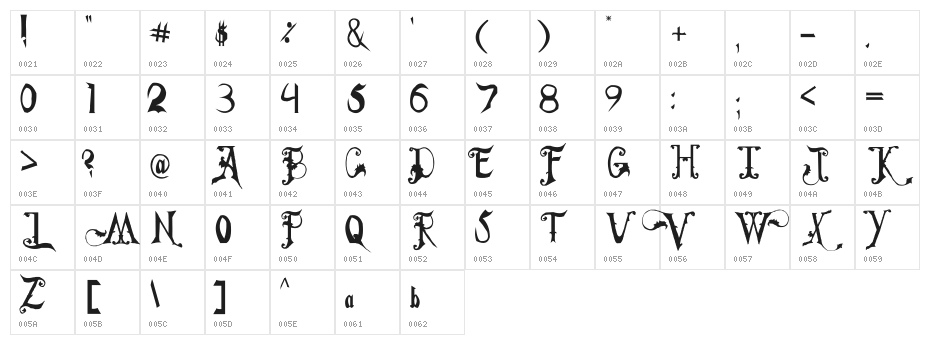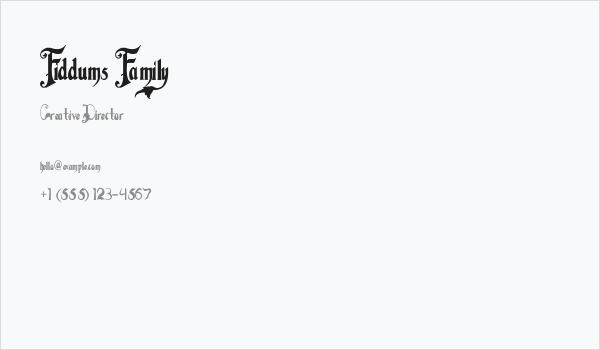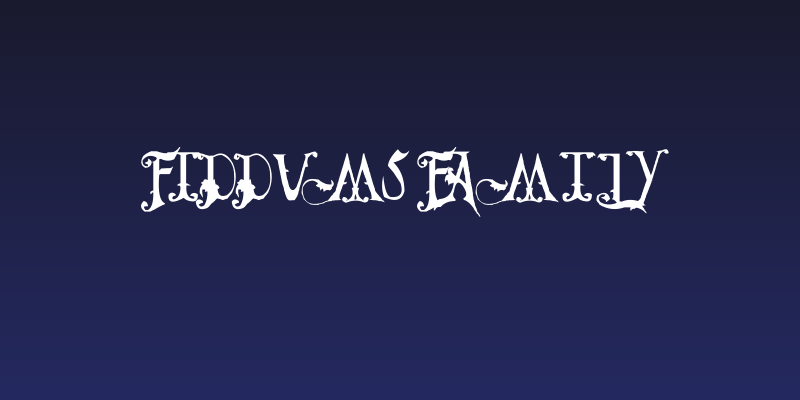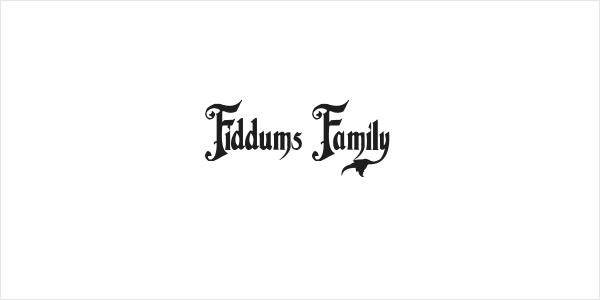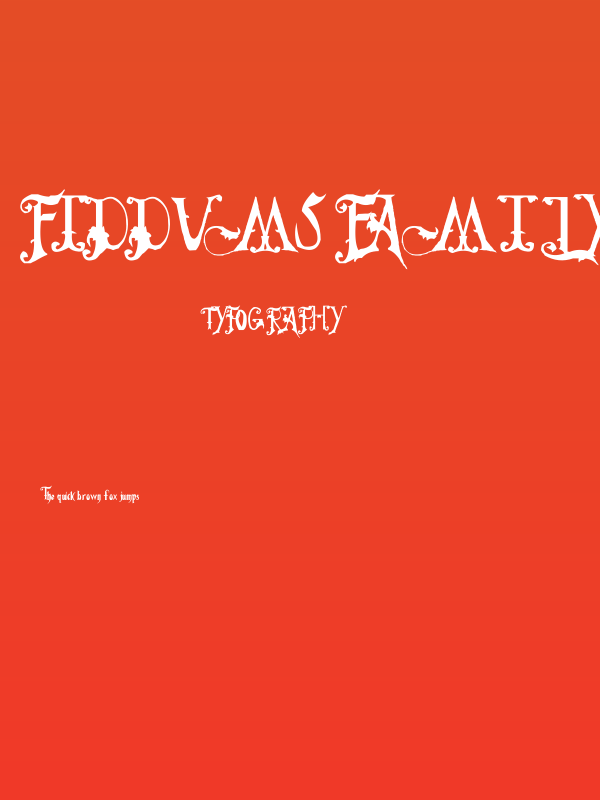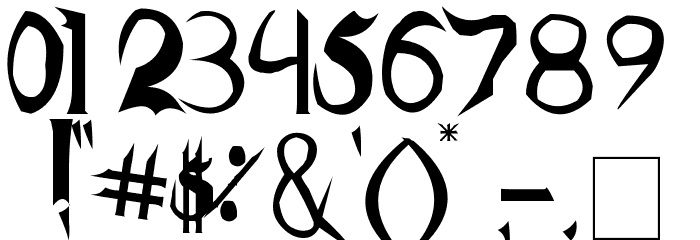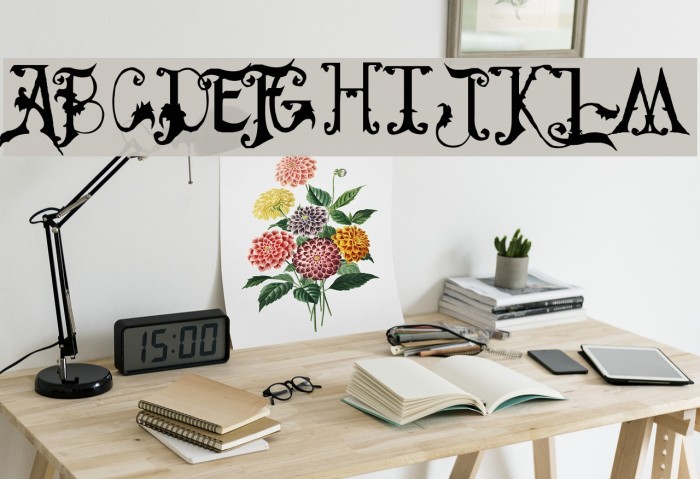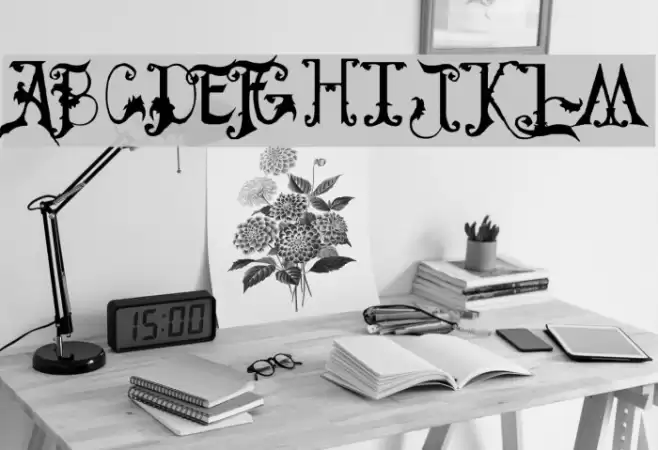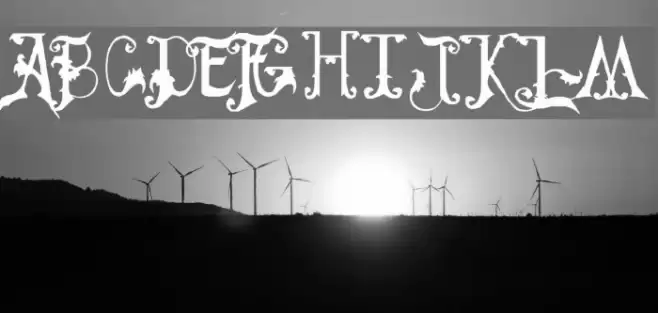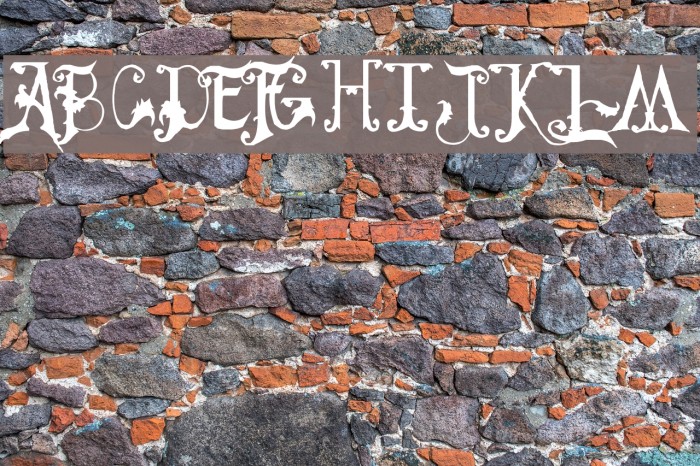
Fiddums Family Font
| Style général | Gothic, Decorative |
| Projets proposés | Ideal for Halloween-themed designs, fantasy book covers, gothic event invitations, and theatrical posters. |